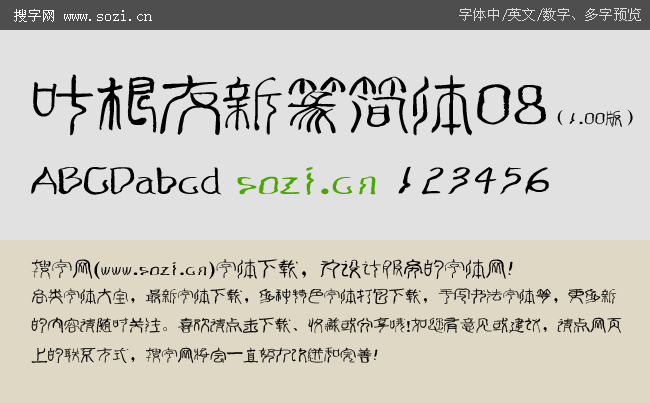
葉根友新篆簡(jiǎn)體
搜字網(wǎng)給大家提供一款葉根友新篆簡(jiǎn)體中文書(shū)法字體下載。葉根友新篆簡(jiǎn)體用于篆體雕刻設(shè)計(jì)方面的字體,字形曲線(xiàn)柔美,直線(xiàn)與曲線(xiàn)有著良好的平衡取舍關(guān)系,適用于藝術(shù)設(shè)計(jì)、繪畫(huà)設(shè)計(jì)、平面廣告等視覺(jué)環(huán)境使用。
• 風(fēng)格類(lèi)別: 篆書(shū)